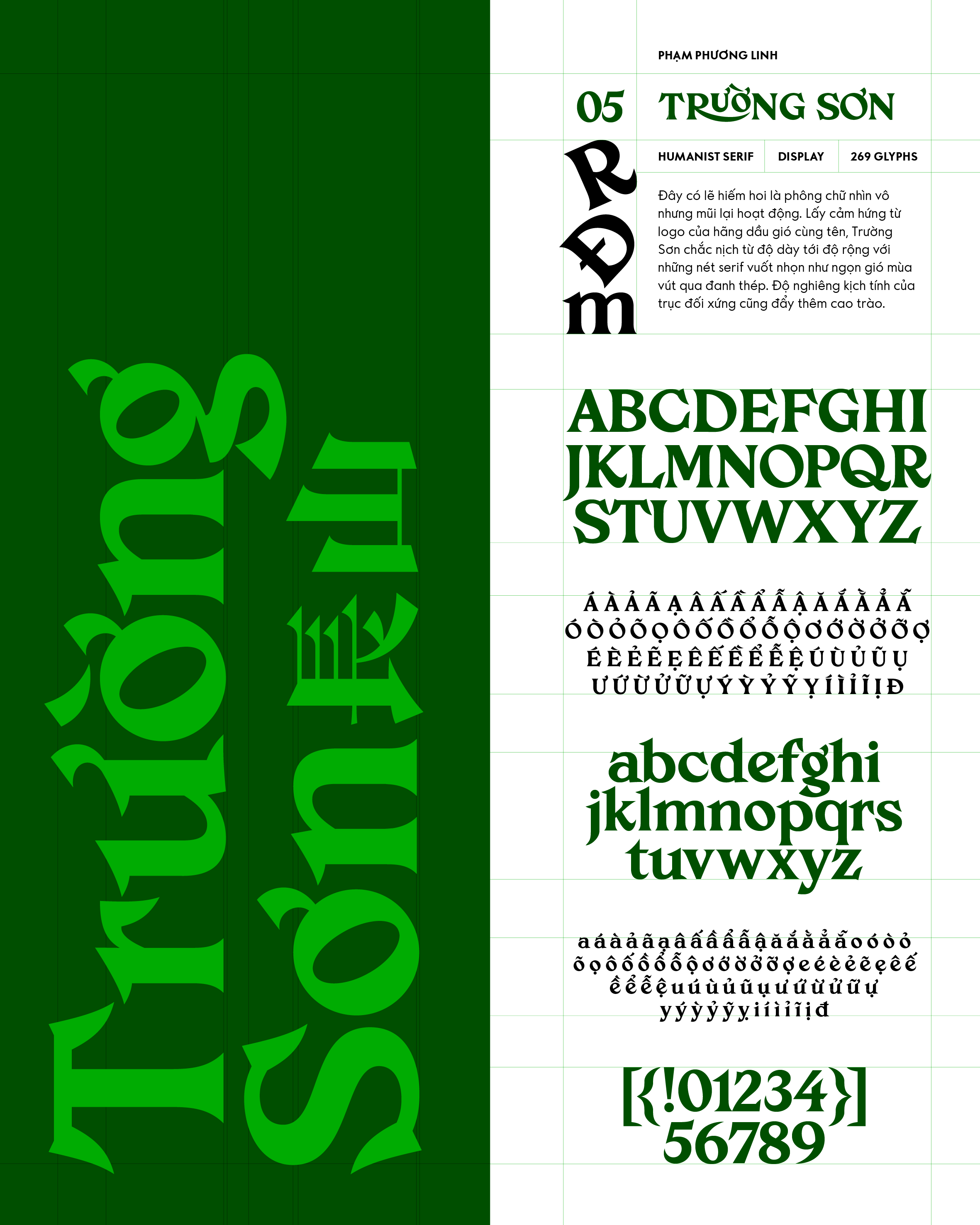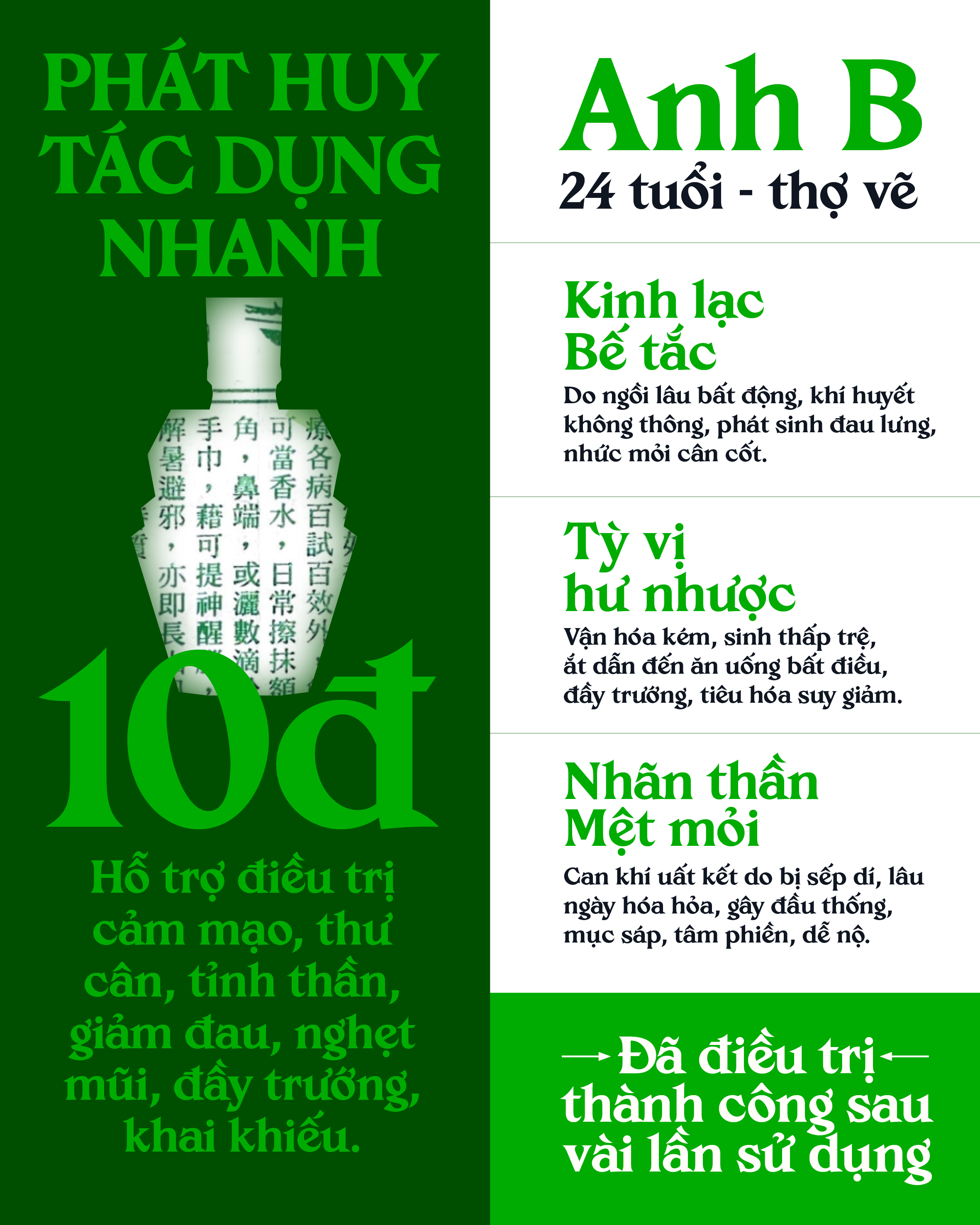
Trường Sơn
Về Trường Sơn: Đây có lẽ hiếm hoi là phông chữ nhìn vô nhưng mũi lại hoạt động. Lấy cảm hứng từ logo của hãng dầu gió cùng tên, Trường Sơn chắc nịch từ độ dày tới độ rộng với những nét serif vuốt nhọn như ngọn gió mùa vút qua đanh thép. Độ nghiêng kịch tính của trục đối xứng cũng đẩy thêm cao trào.
Humanist Serif
Display
Phương Linh
Trường Sơn
Battlefield
Trường Sơn
Utmost Speed
Trường Sơn
Bổ long não
Trường Sơn
Phát huy tác dụng tức thời
Trường Sơn
Dầu gió Trường Sơn là một loại dầu xoa quen thuộc trong đời sống người Việt, gắn liền với ký ức gia đình và thói quen chăm sóc sức khỏe hàng ngày.
Trường Sơn
Với mùi hương đặc trưng từ bạc hà, khuynh diệp và các tinh dầu khác, dầu thường được dùng để giảm đau đầu, chóng mặt, cảm lạnh hoặc côn trùng cắn bằng cách thoa trực tiếp lên da. Không chỉ là một sản phẩm y học dân gian tiện lợi, dầu gió Trường Sơn còn mang tính biểu tượng văn hóa, xuất hiện trong túi xách của nhiều thế hệ như một “vật bất ly thân.” Tên gọi “Trường Sơn” cũng gợi nhắc đến lịch sử và tinh thần thời chiến, khiến sản phẩm này không chỉ đơn thuần là dầu xoa mà còn mang theo một lớp ký ức tập thể, kết nối giữa quá khứ và đời sống hiện tại.